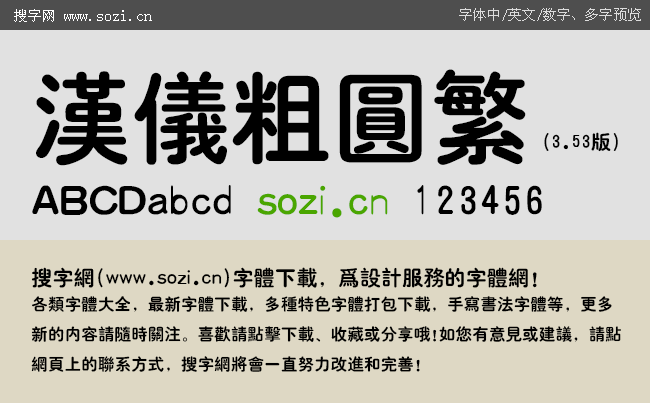
漢儀粗圓繁3.53版
搜字網(wǎng)提供一款漢儀粗圓繁字體下載,該字體每個(gè)漢字都經(jīng)過精心設(shè)計(jì),筆畫粗細(xì)均勻、結(jié)構(gòu)美觀。每個(gè)字的圓角、圓頭、勾形都極光潔、風(fēng)格統(tǒng)一,字形放大不變形,縮小顯示清晰,適用于樣本畫冊,報(bào)紙排版,網(wǎng)頁標(biāo)題等廣告設(shè)計(jì)應(yīng)用。